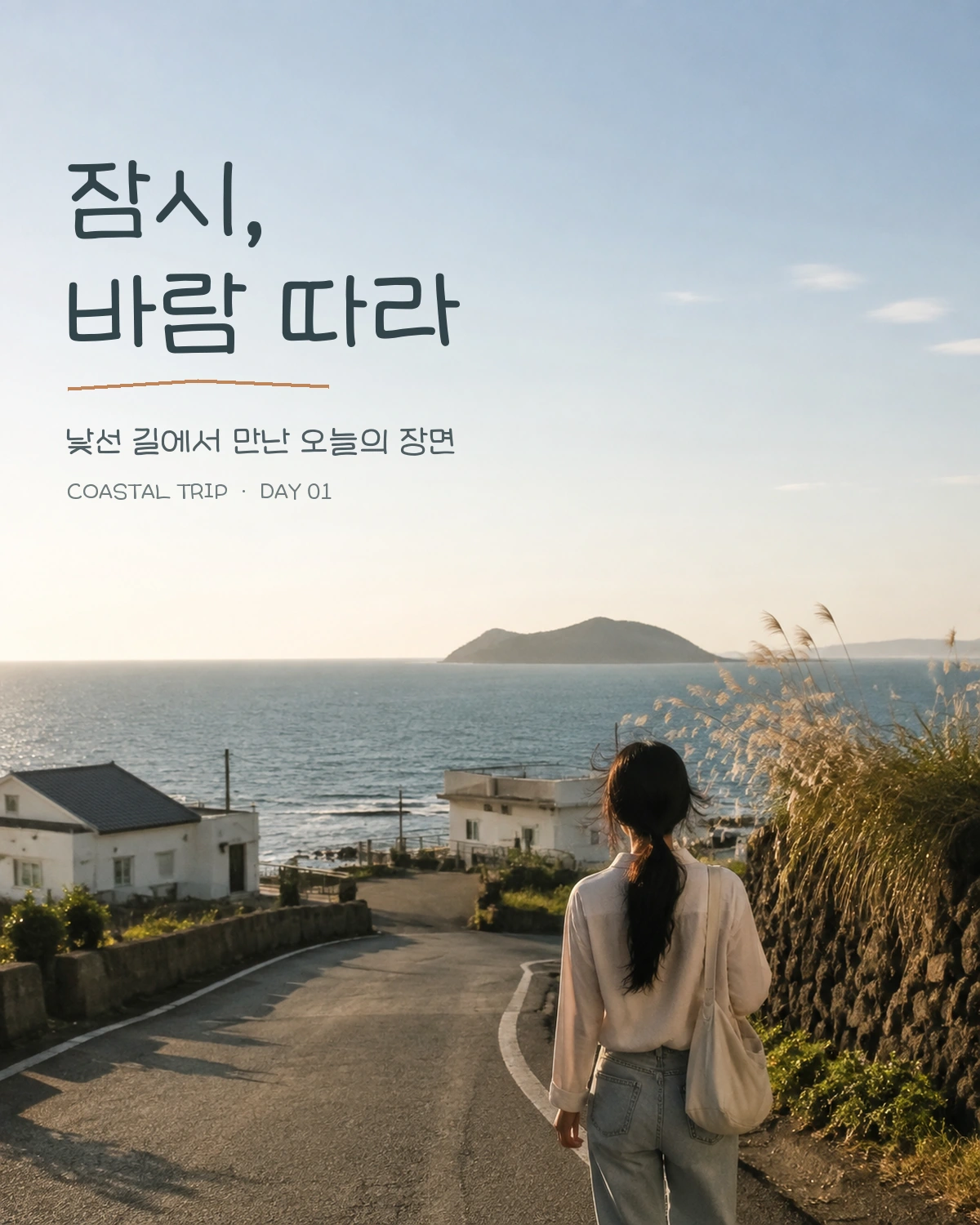
이서윤체 — 흥국생명에서 배포하는 무료 폰트입니다. 손글씨 공모전 최우수작을 그대로 옮긴 서체로, 따뜻하고 자연스러운 결이 남아 있는 손글씨체
흥국생명이 2021년에 연 제1회 디지털 손글씨 공모전에서 최우수상을 받은 세 사람 가운데 한 명의 손글씨를 서체로 옮긴 글꼴입니다. 공모 주제는 나에게 하고 싶은 말이었고 약 900점이 출품됐습니다. 2022년 1월에 무료로 공개됐습니다.
같은 공모전에서 나온 자매 서체가 둘 더 있습니다. 심경하체와 전화선체입니다. 세 벌이 한 세트로 배포됩니다.
흥국생명이 직접 쓴 조형 설명은 따로 공개돼 있지 않습니다. 파일에서 재어 보면 받침이 붙어도 높이가 크게 변하지 않는 네모틀이고 낱자는 가로로 넓게 퍼져 있어, 손글씨치고는 글줄이 가지런한 편입니다. 굵기는 하나이고 현대 한글 11,172자를 모두 담았습니다. 문서와 인쇄물, 웹, 영상, CI와 BI, 임베딩까지 폭넓게 허용되지만 폰트를 고치거나 다시 배포하는 것은 금지됩니다.